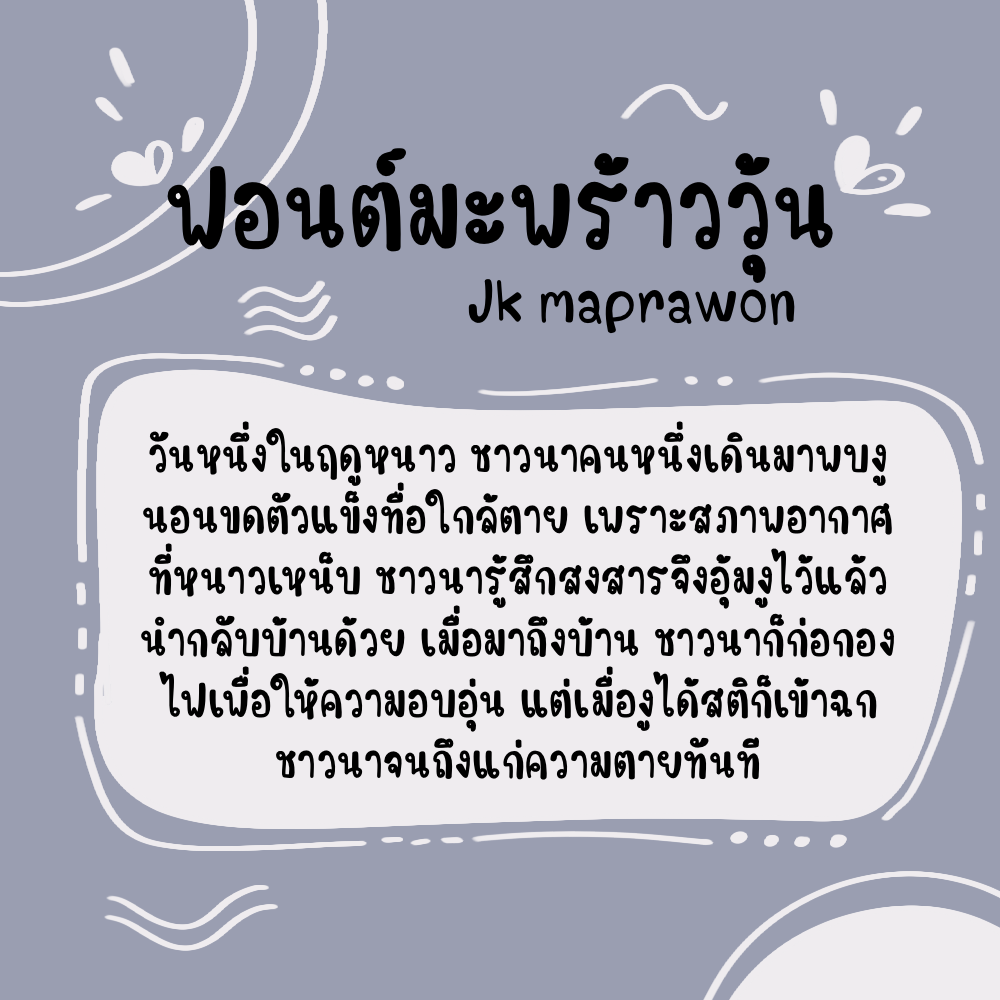
มะพร้าววุ้น (JK Maprawon)
ฟอนต์ มะพร้าววุ้น (JK Maprawon) ฟอนต์ที่มีเอกลักษณ์ ใช้ทำงานสไตล์น่ารักๆ จดโน้ต หรือจะทำแฟลชการ์ดก็ดูดี แจกฟรีไปเลยเวอร์ชันทดลอง : แบบปกติ 1 น้ำหนัก ใช้ได้เฉพาะแบบส่วนตัว เช่น ใช้ในการศึกษา ใช้จด ใช้ตกแต่งสมุดโน้ตตัวเอง